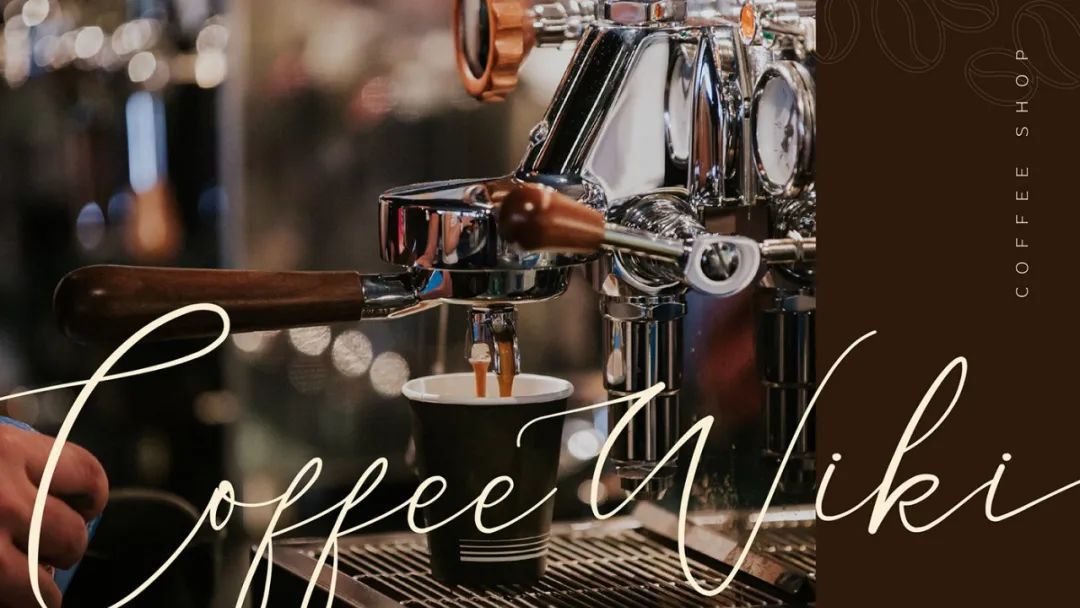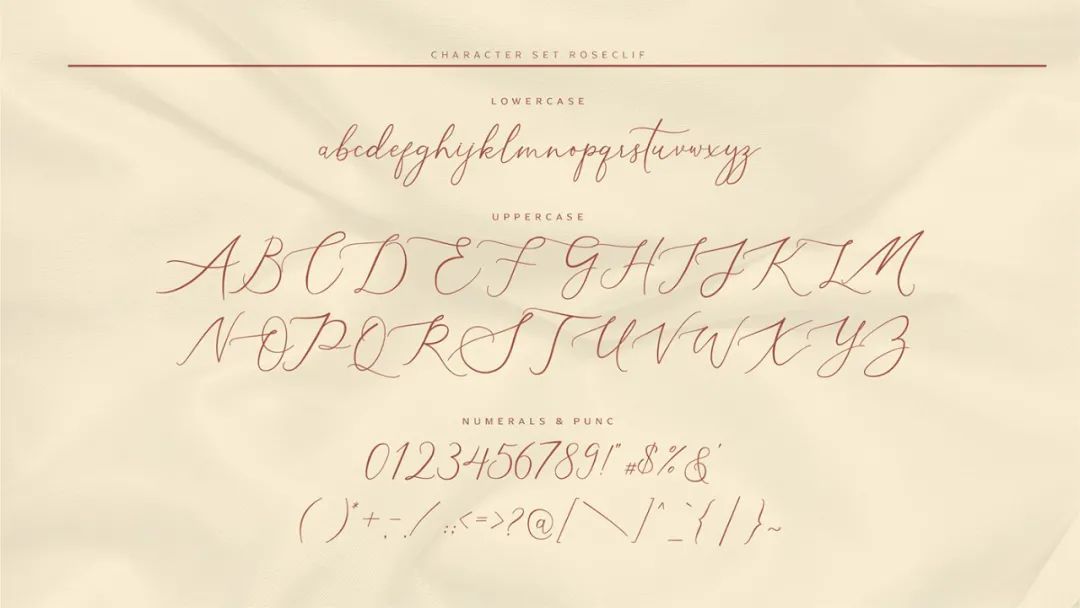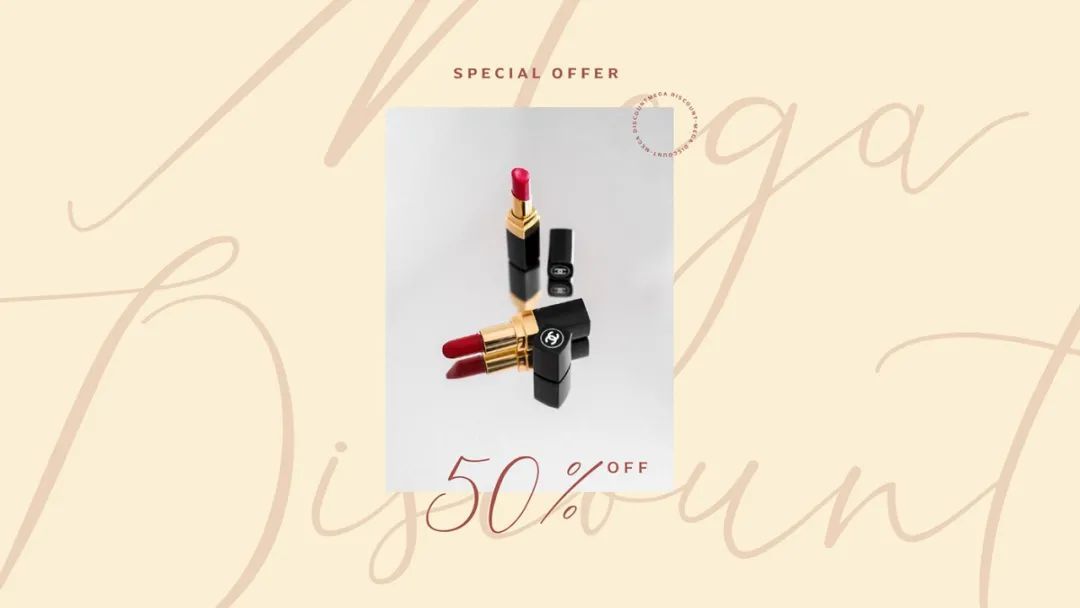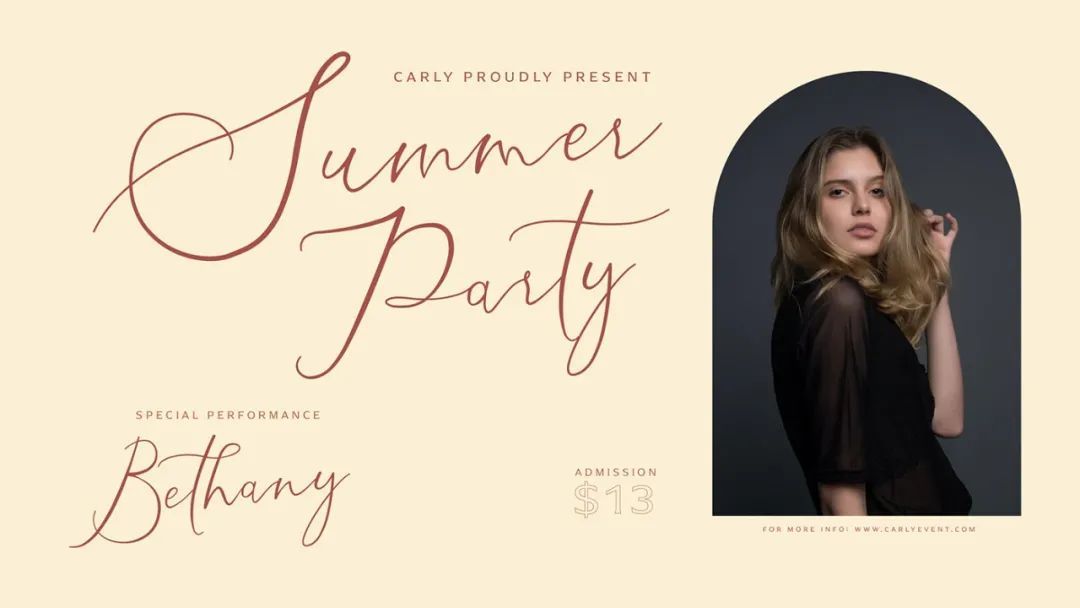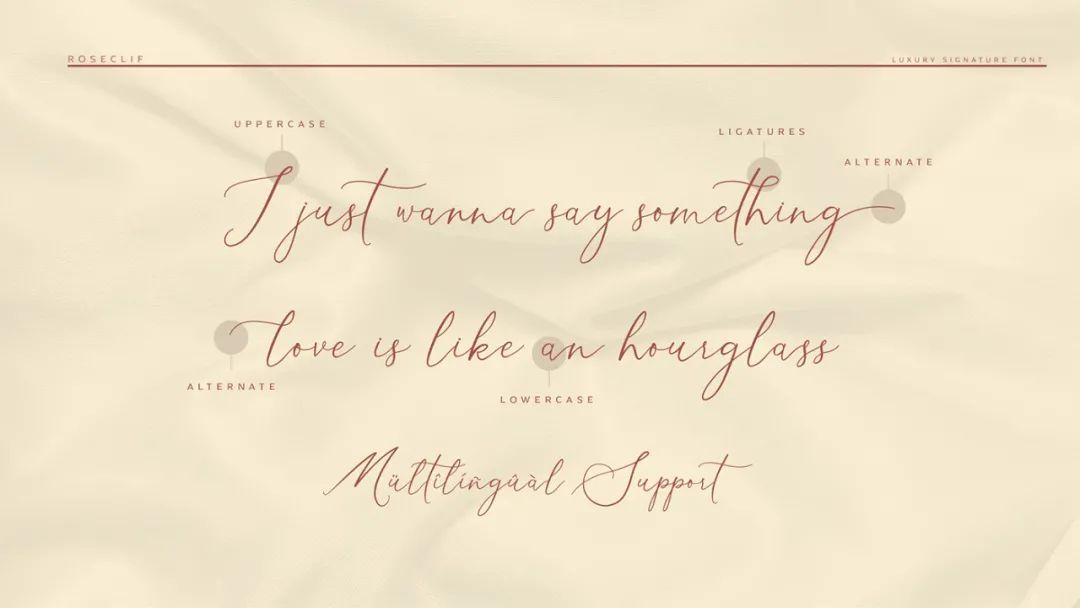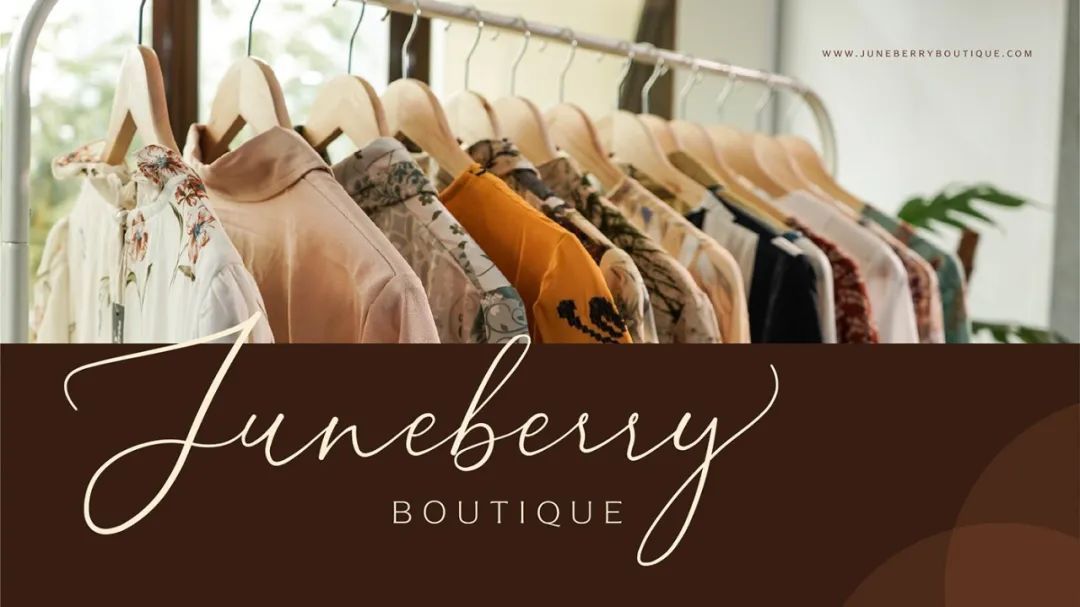
一款自然手绘风的签名字体
今天和大家推荐一款来自 firstype studio 工作室的字库作品——Roseclif 手写体。
Roseclif 手写体是一款基于自然手绘签名风格的签名字体,略显豪华。Roseclif 的opentype 功能包括连字和风格选择,让你可以混合和匹配您选择的字母,从而做出满意的设计作品。这种字体还支持多种语言!